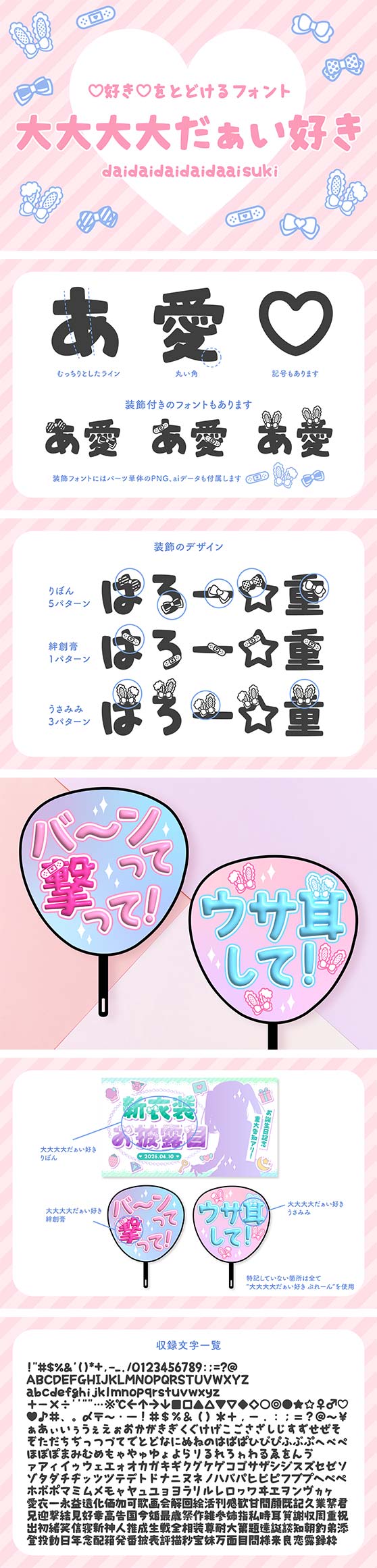
大大大大だぁい好き 4書体セット
コンセプトは「好きを届けるフォント」
「大大大大だぁい好き」は、推しを応援したい、または自分を推してほしい、そんな場面で使いたくなるフォントファミリー。
ぷれーん、りぼん、絆創膏、うさみみをフル収録したお得な4書体セットです。
ひらがな、カタカナ、英数、一部の記号、一部の漢字(推し活やサムネイルの見出しに使いやすい文字を厳選した115字)